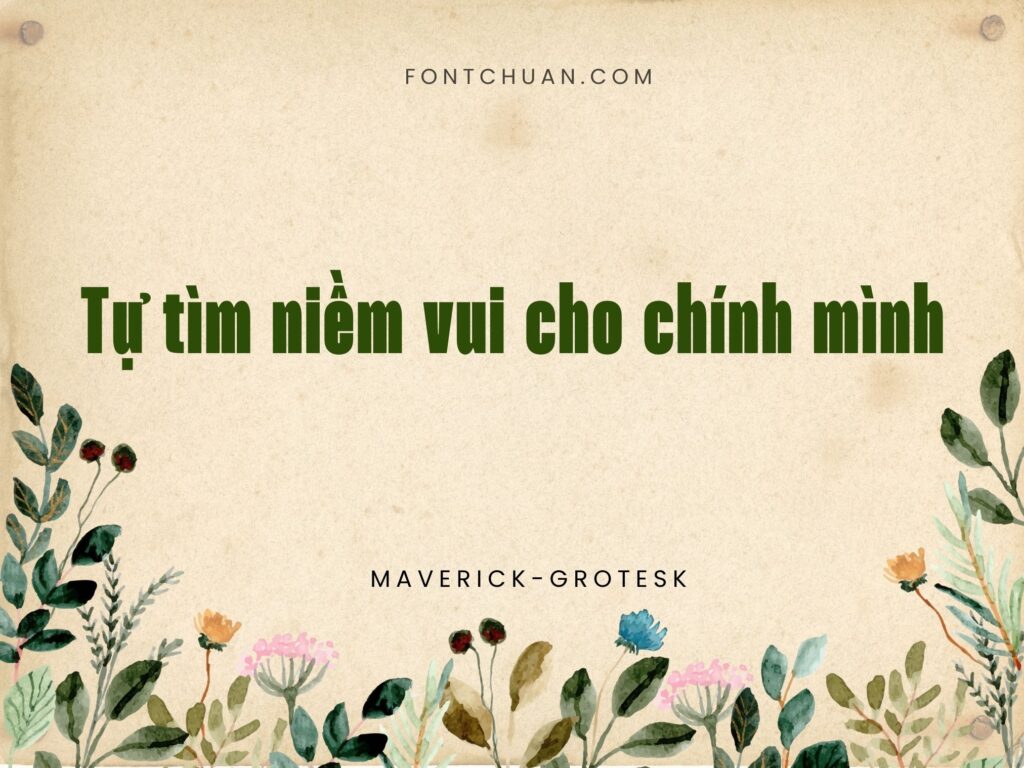
Maverick Grotesk là một font sans-serif dạng condensed với phong cách hiện đại, được thiết kế bởi 26MARCH. Với chiều rộng hẹp và các ký tự cao, font này là lựa chọn lý tưởng để lấp đầy những không gian chật hẹp hoặc nhiều dòng chữ. Maverick Grotesk hỗ trợ tiếng Việt và nhiều ngôn ngữ khác, được sưu tầm và đăng bởi thành viên của Font Chuẩn.
Font có cấu trúc chữ rõ ràng, độ dày nét đồng nhất và các đường nét tinh tế, tạo nên sự cân bằng giữa tính thẩm mỹ và khả năng đọc. Maverick Grotesk phù hợp cho các thiết kế liên quan đến thương hiệu, truyền thông xã hội, tiêu đề và nội dung số. Các ngành nghề như quảng cáo, công nghệ, giáo dục và bất động sản có thể tận dụng hiệu quả font này. Ngoài ra, Maverick Grotesk cũng thích hợp cho các sự kiện như lễ hội, sinh nhật, ngày Nhà giáo và Valentine.